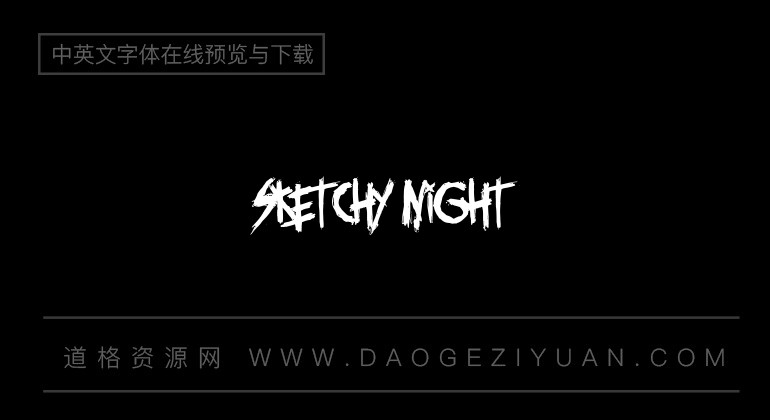
Sketchy Night 是一种手写风格的字体,其特点是线条不太规则、有些粗细不一,给人一种随意、自然的感觉。 Sketchy Night 字体由 Dustin Lee 设计,有两种版本:Sketchy Night Regular 和 Sketchy Night Bold。这两个版本都包含大写和小写字母、数字、标点符号和其他特殊字符。 这种字体适合用于卡通、漫画或手绘风格的设计,如海报、标志、产品包装、网站设计等等。它可以为设计师带来一种个性化的、手工制作的感觉,让他们的设计更具创意和吸引力。内容介绍
Sketchy Night是一款非常不错的手写艺术字体,具有很好的视觉感,适合于文化类的宣传设计、商业类品牌的广告和产品包装设计以及个性化文字排版等较多场景。